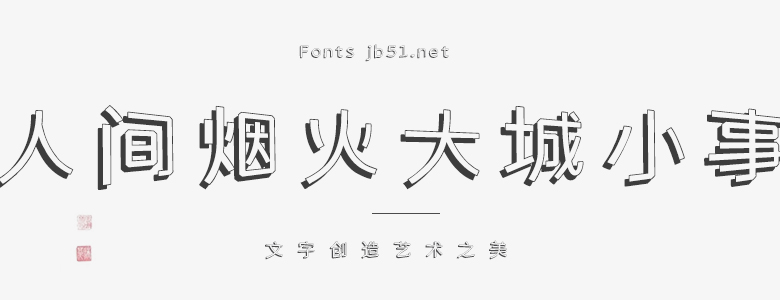
人間煙火大城小事是一款獨(dú)特且富有藝術(shù)性的字體,它的設(shè)計(jì)理念源于我們對(duì)日常生活細(xì)致入微的觀察和對(duì)城市生活獨(dú)特魅力的感悟。字體中融入了都市的喧囂、繁華與煙火氣息,將大城小事中那種鮮活的生活氣息展現(xiàn)得淋漓盡致。 這款字體筆畫流暢,結(jié)構(gòu)簡(jiǎn)潔,每一個(gè)字母、每一個(gè)筆畫都經(jīng)過(guò)精細(xì)的打磨和設(shè)計(jì)。其線條有一種動(dòng)態(tài)感,仿佛在空氣中畫出了一幅城市生活的流動(dòng)畫卷。每個(gè)字母的形狀都帶有一種獨(dú)特的藝術(shù)感,充滿了生活的色彩和溫度。 人間煙火大城小事非常適合用于設(shè)計(jì)項(xiàng)目中,無(wú)論是品牌形象、廣告宣傳還是產(chǎn)品包裝,都能夠展現(xiàn)出獨(dú)特的風(fēng)格和個(gè)性。同時(shí),這款字體的可讀性也非常強(qiáng),即使在較小的字號(hào)下,也能夠清晰地傳達(dá)信息。 總的來(lái)說(shuō),人間煙火大城小事是一款充滿生活氣息和藝術(shù)感的字體,它將城市的繁華與生活的煙火完美地融合在一起,無(wú)論是從視覺(jué)上還是從情感上,都能夠給人帶來(lái)深刻的印象。